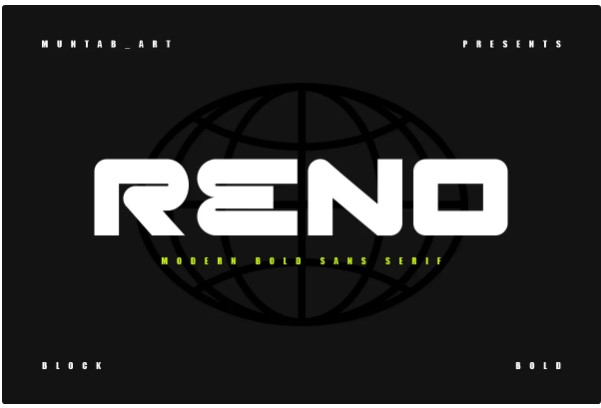
Creativemarket Reno Font
[Creativemarket] Reno Font
Шрифт Reno включает прописные буквы, цифры, большой набор знаков препинания.
Шрифт Sans serif с современным стилем. Создан для плакатов, веб-дизайна, брендинга, иллюстраций, значков и некоторых других работ.